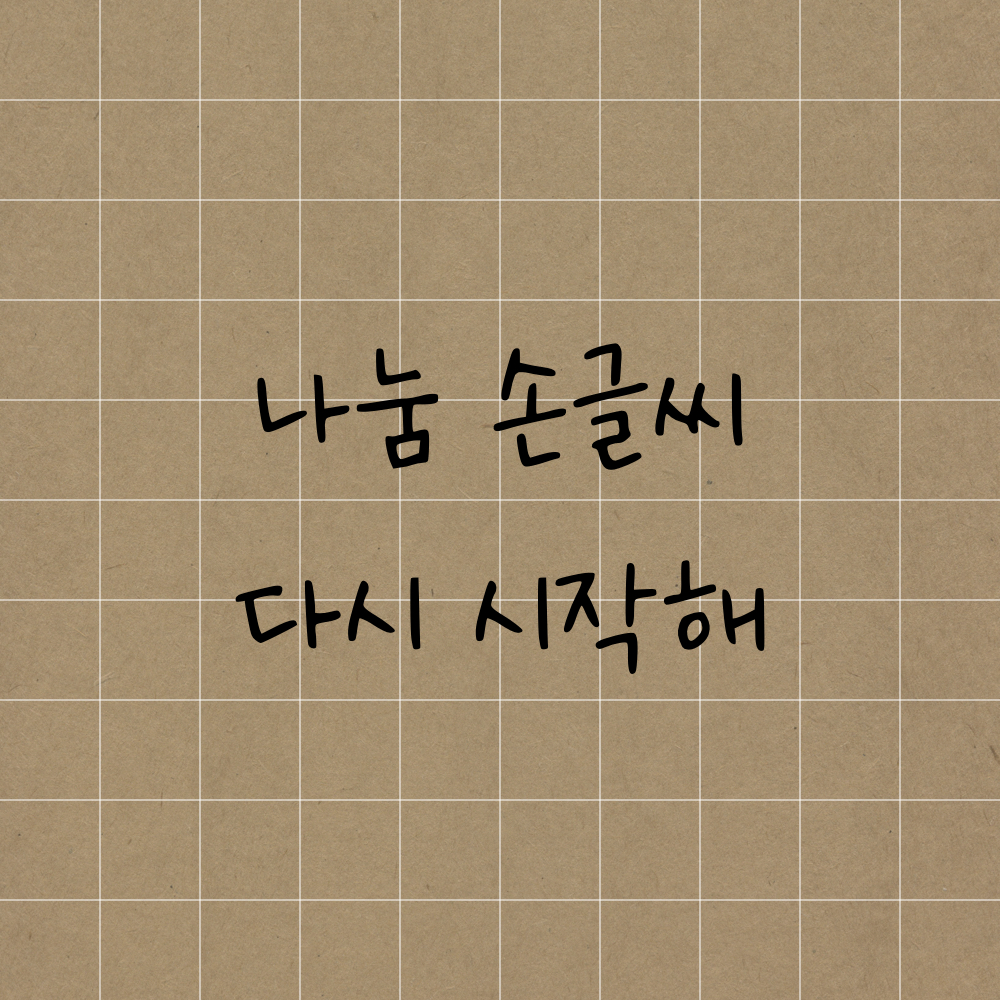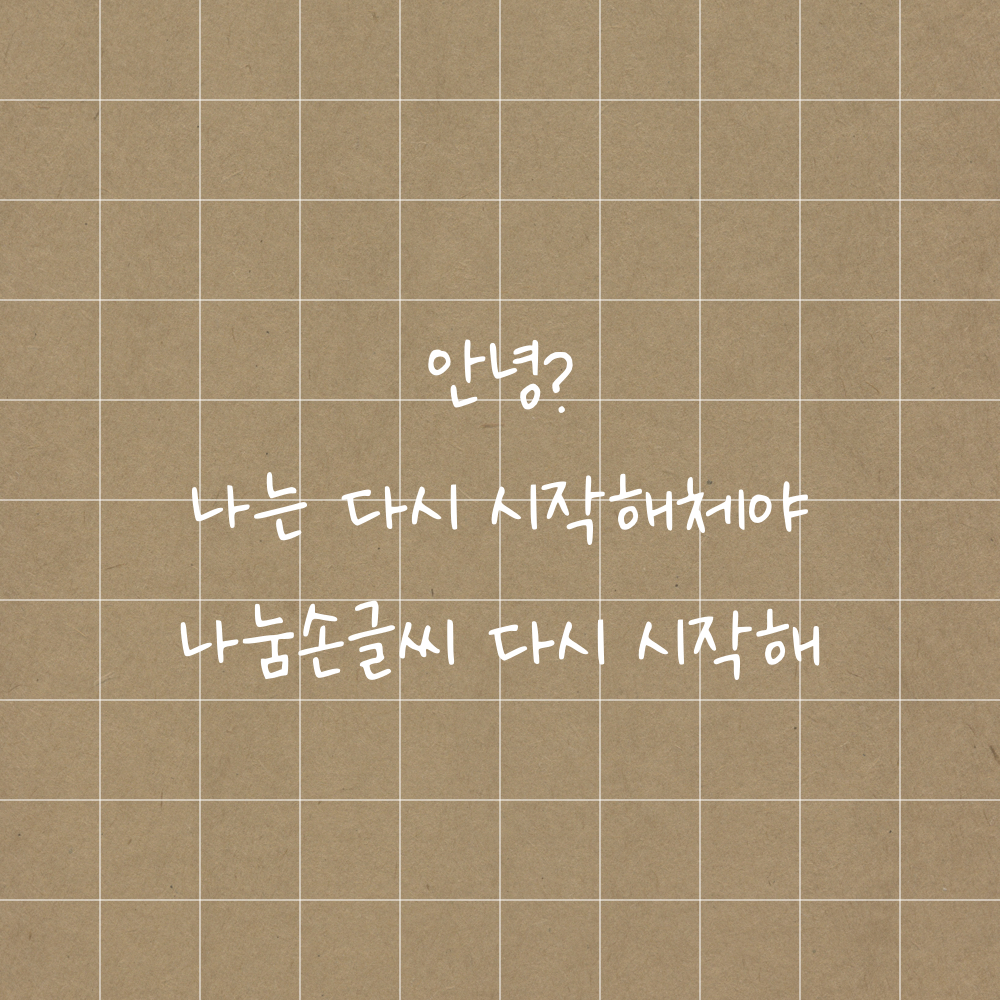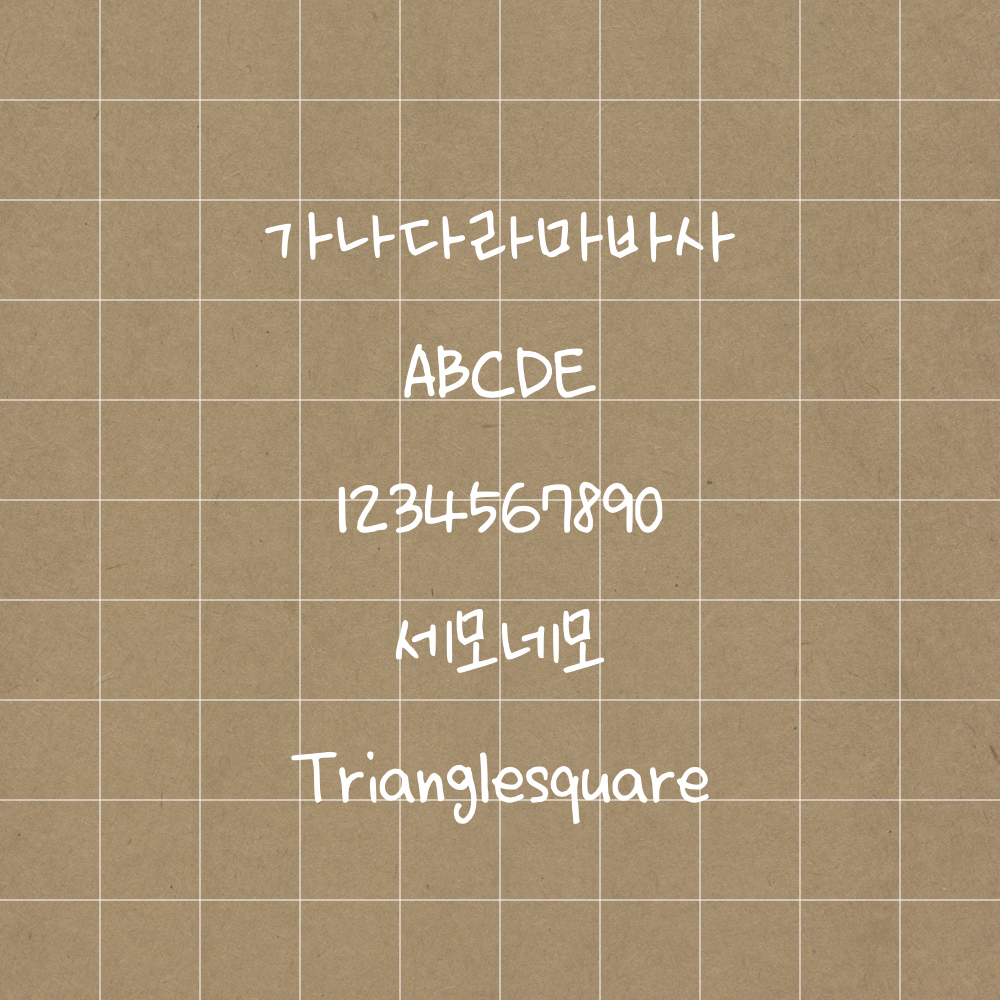
오늘의 폰트는 다시 시작해체입니다😎
블로거라면 모르기 어려운 폰트죠😁 이제 태블릿에도 적용할 수 있습니다.
이번엔 폰트를 알아보겠습니다😍
본 적 있는 익숙한 폰트죠~?🙂
한국인이라면, 검색을 자주 한다면 모를 수 없는 폰트😁
오늘부터 굿노트에 적용해서 아기자기한 다꾸를 즐겨보는 건 어떤가요~?🫶